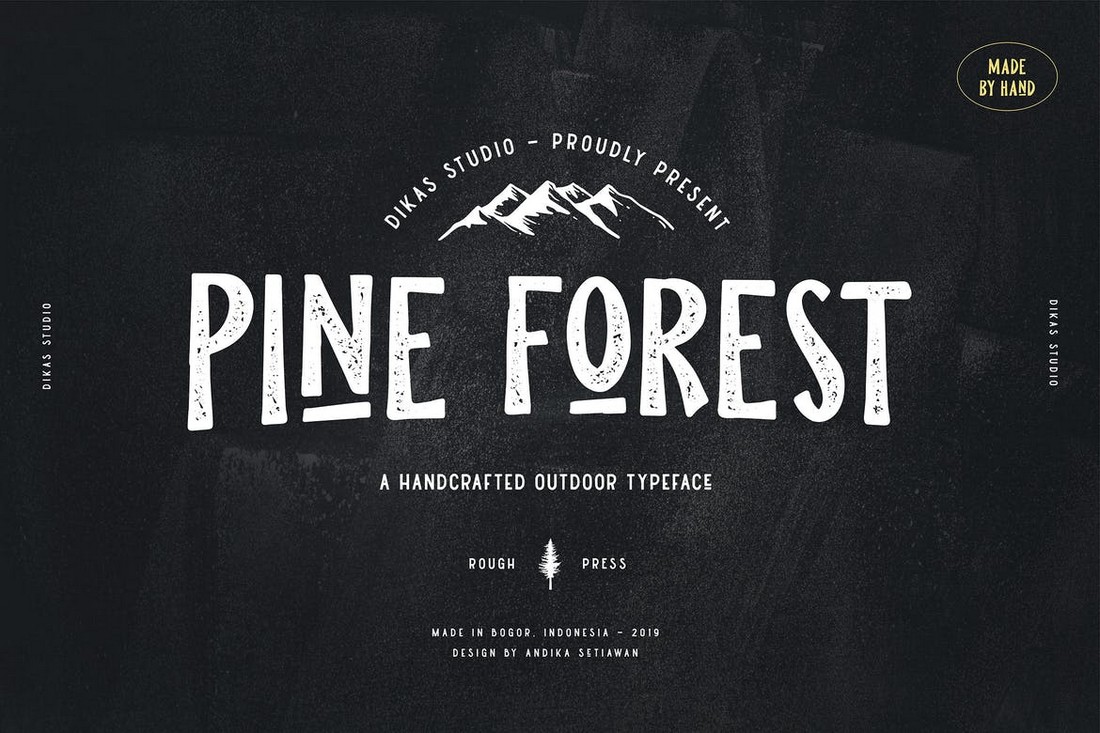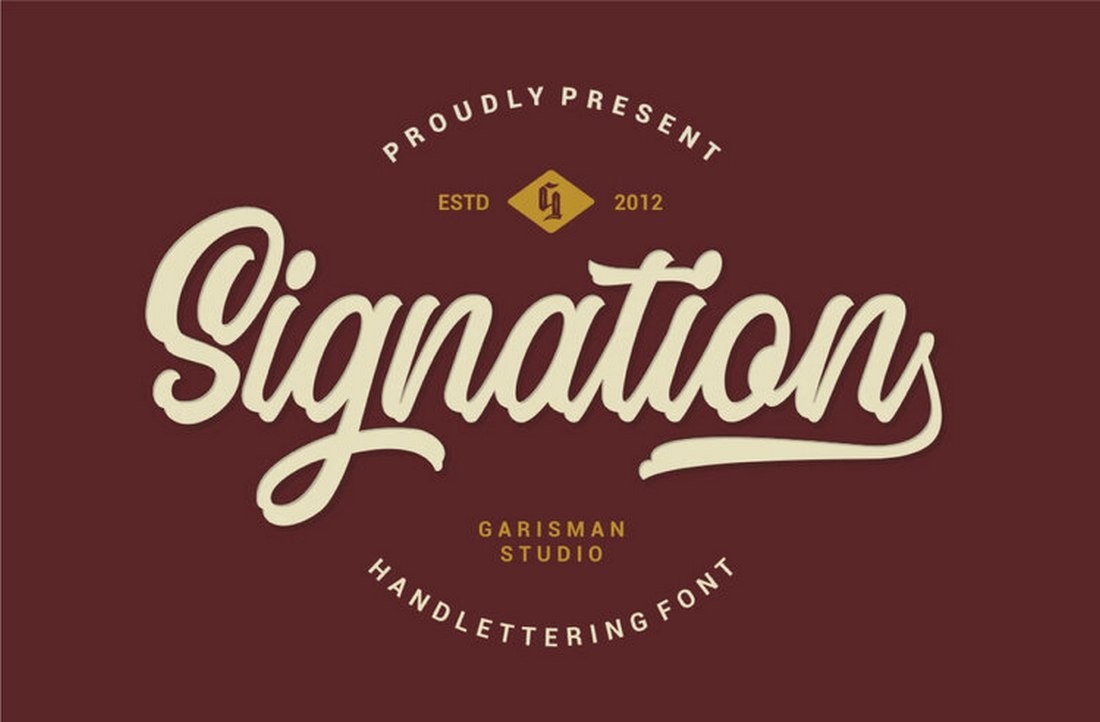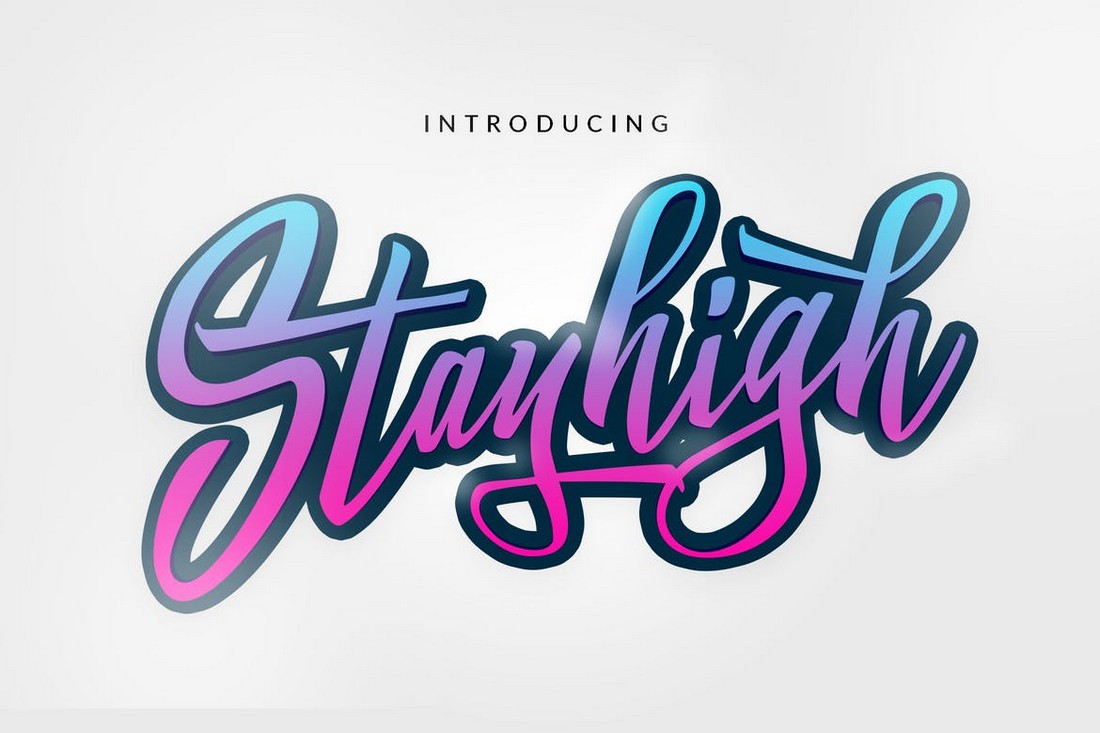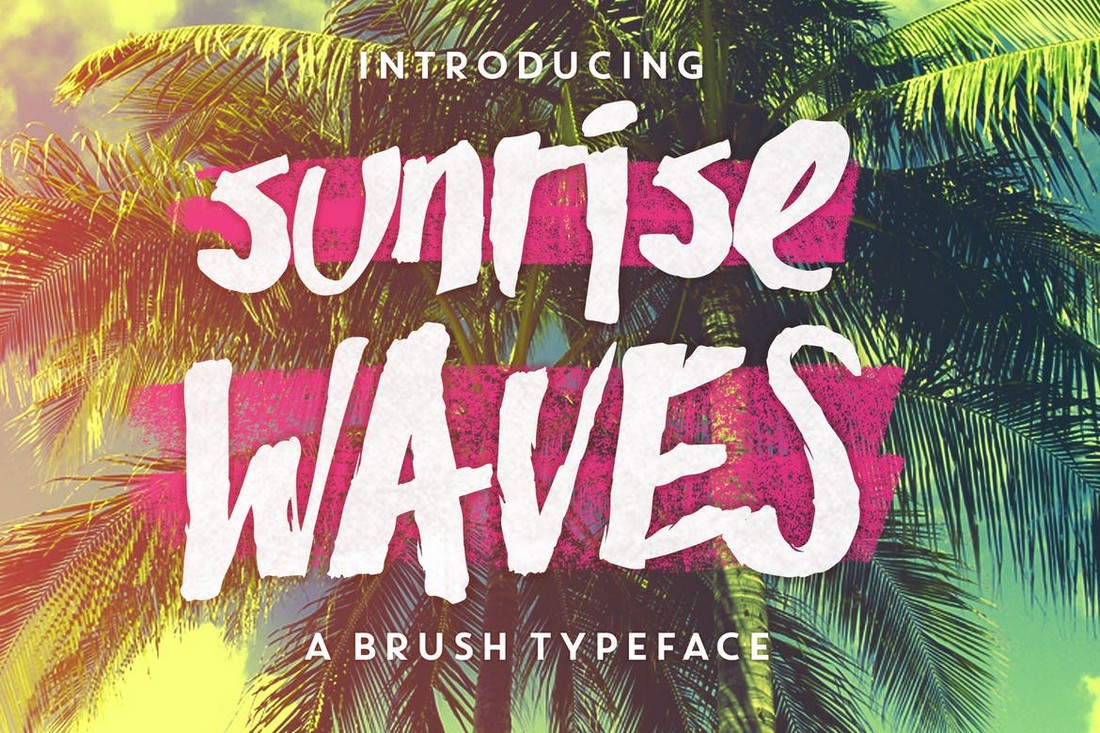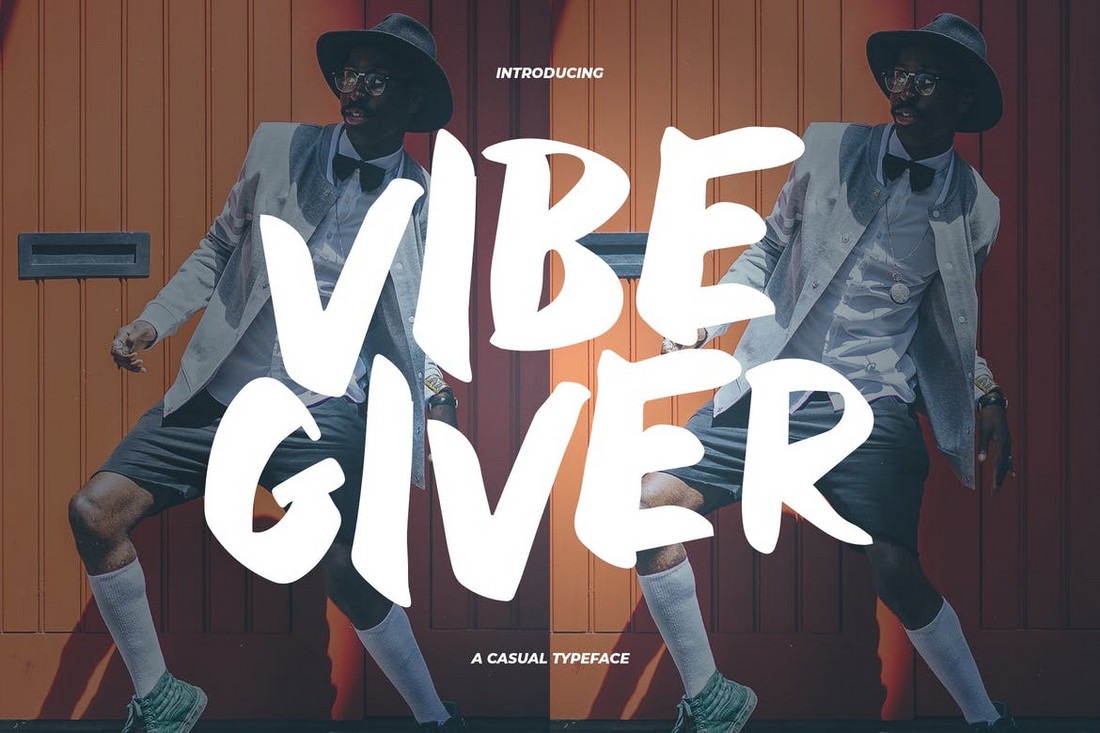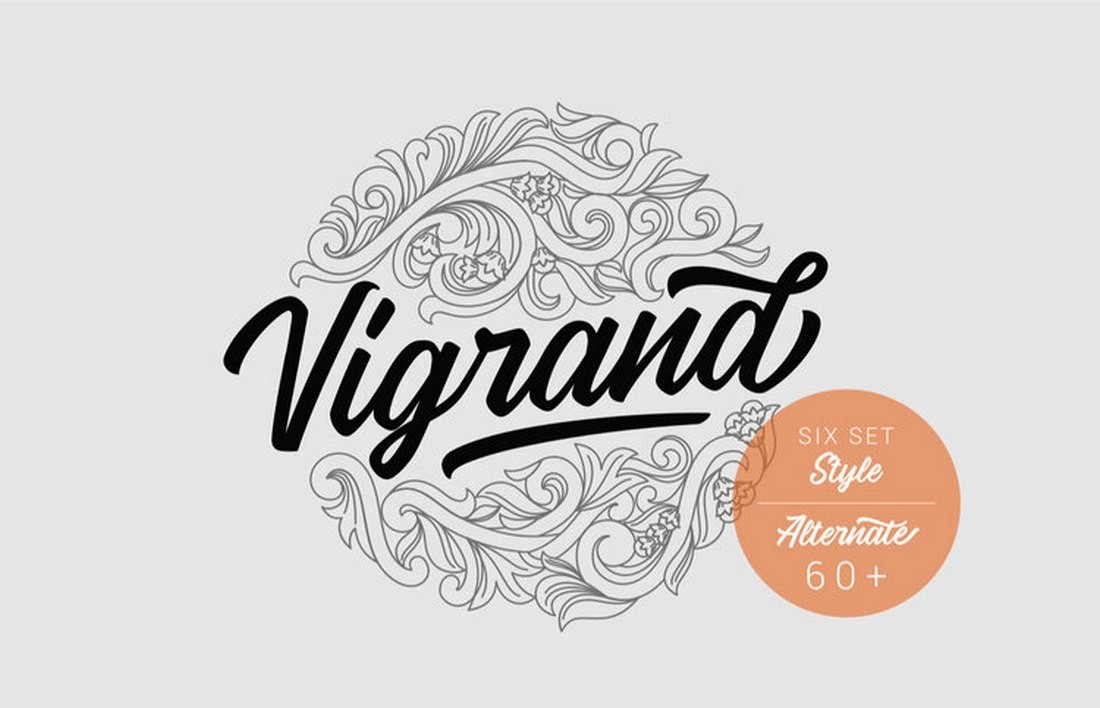
你對(duì)你的海報(bào)、T恤衫以及其他平面項(xiàng)目中的字體選擇滿意嗎? 今天我們精選了以系列獨(dú)特的字體,希望可以幫助你的項(xiàng)目找到合適的字體。
如今,定制類的T恤很受歡迎。 實(shí)際上,許多設(shè)計(jì)師目前通過使用Shopify等平臺(tái)在線銷售自己獨(dú)特的T恤來謀生。 只需要一個(gè)很棒的字體和一個(gè)合適的報(bào)價(jià)就可以制造出暢銷的T恤。
字體尤其在T恤設(shè)計(jì)中起著關(guān)鍵作用。 它需要看起來時(shí)尚并能夠引起觀眾的共鳴才能真正吸引他們的注意力。 你需要一種具有獨(dú)特設(shè)計(jì)的字體才能實(shí)現(xiàn)該目標(biāo)。
我們發(fā)現(xiàn)了一些可用于制作吸引人的T恤設(shè)計(jì)的獨(dú)特字體。 這些字體非常適合制作各種類型的T恤,從時(shí)髦的連帽衫到休閑T恤,背心等等。
1.Stay High – Stylish Urban T-Shirt Font
Stay High是一款創(chuàng)意的,獨(dú)特的字體。 非常適合制作吸引注意力的T恤以及醒目的大號(hào)標(biāo)題。 字體帶有手寫樣式設(shè)計(jì),以及200個(gè)字形和多語言支持。
2.Sunrise Waves – Unique T-Shirt Font
看到此字體時(shí),你會(huì)想到的第一個(gè)念頭是溫暖的夏日微風(fēng)。 Sunrise Waves是制作和設(shè)計(jì)時(shí)尚的夏季主題T恤甚至獨(dú)特的襯衫設(shè)計(jì)的完美字體。
3.Author Type – Handmade Brush Font
Author Type是一款基于手工風(fēng)格的字體,設(shè)計(jì)簡(jiǎn)潔休閑。 這種獨(dú)特的字母風(fēng)格使其在人群中能夠脫穎而出,你的T恤設(shè)計(jì)也會(huì)如此。 字體包括大寫和小寫字母,以及用于樣式的斜線。
4.Chillvornia – Vintage Condensed Font
該字體具有經(jīng)典的復(fù)古字母設(shè)計(jì),可讓你根據(jù)各種主題和目的來制作時(shí)尚的T恤設(shè)計(jì)。 字體有2種不同的樣式,也可以結(jié)合使用以創(chuàng)建更多內(nèi)容。
5.Pine Forest – Handcrafted T-Shirt Font
Pine Forest是一種手工制作的字體,帶有粗糙的紋理設(shè)計(jì)。 該字體非常適合用于制作T恤的徽章和標(biāo)題。 它具有非常有創(chuàng)意的字體設(shè)計(jì),也可以為你的設(shè)計(jì)添加個(gè)性化外觀。
6.Vigrand – Free Stylish T-Shirt Font
Vigrand是一款時(shí)尚的字體,具有現(xiàn)代時(shí)尚的設(shè)計(jì)。 字體有6種不同的樣式,所有字體均可免費(fèi)用于你的個(gè)人項(xiàng)目。
7.Signation – Free Classic T-Shirt Font
Signation是一款優(yōu)雅的手寫腳本字體,帶有經(jīng)典的復(fù)古設(shè)計(jì)。 該字體非常適合用于設(shè)計(jì)T恤的徽章。 你可以免費(fèi)下載并用于個(gè)人項(xiàng)目。
8.Stanley – Creative Script & Sans Font Duo
Stanley是兩種獨(dú)特字體的集合,其中包括腳本字體和常規(guī)的sans-serif字體。 可用于創(chuàng)建時(shí)尚的口號(hào)或標(biāo)題以及徽章等,這兩種字體可以很好地進(jìn)行配對(duì)。 你可以使用此字體包來制作自己的驚人T恤設(shè)計(jì)。
9.RailBrush – Trendy T-Shirt Font
這種手寫字體具有非常獨(dú)特的字符設(shè)計(jì)。 創(chuàng)意和有趣的字體也使該字體成為制作T恤的理想選擇。 經(jīng)過優(yōu)化,可以在各種字體大小下正常工作。
10.VibeGiver – Casual T-Shirt Font
這種字體的字符設(shè)計(jì)是一個(gè)常見的樣式,但是這也是使它變得更好的原因。 該字體具有獨(dú)特的大字體設(shè)計(jì)和原始外觀。 非常適合各種休閑T恤設(shè)計(jì)。
總結(jié)
這就是我們一系列的美麗而富啟發(fā)性的字體和字體集合。 文章(https://designshack.net/articles/inspiration/best-fonts-for-t-shirts/)中推薦的字體適用于海報(bào),邀請(qǐng)函,T恤甚至是網(wǎng)站設(shè)計(jì)等數(shù)字化項(xiàng)目以及其中的所有內(nèi)容! 使用這些集合之一為你的下一個(gè)設(shè)計(jì)項(xiàng)目找到理想的字體。